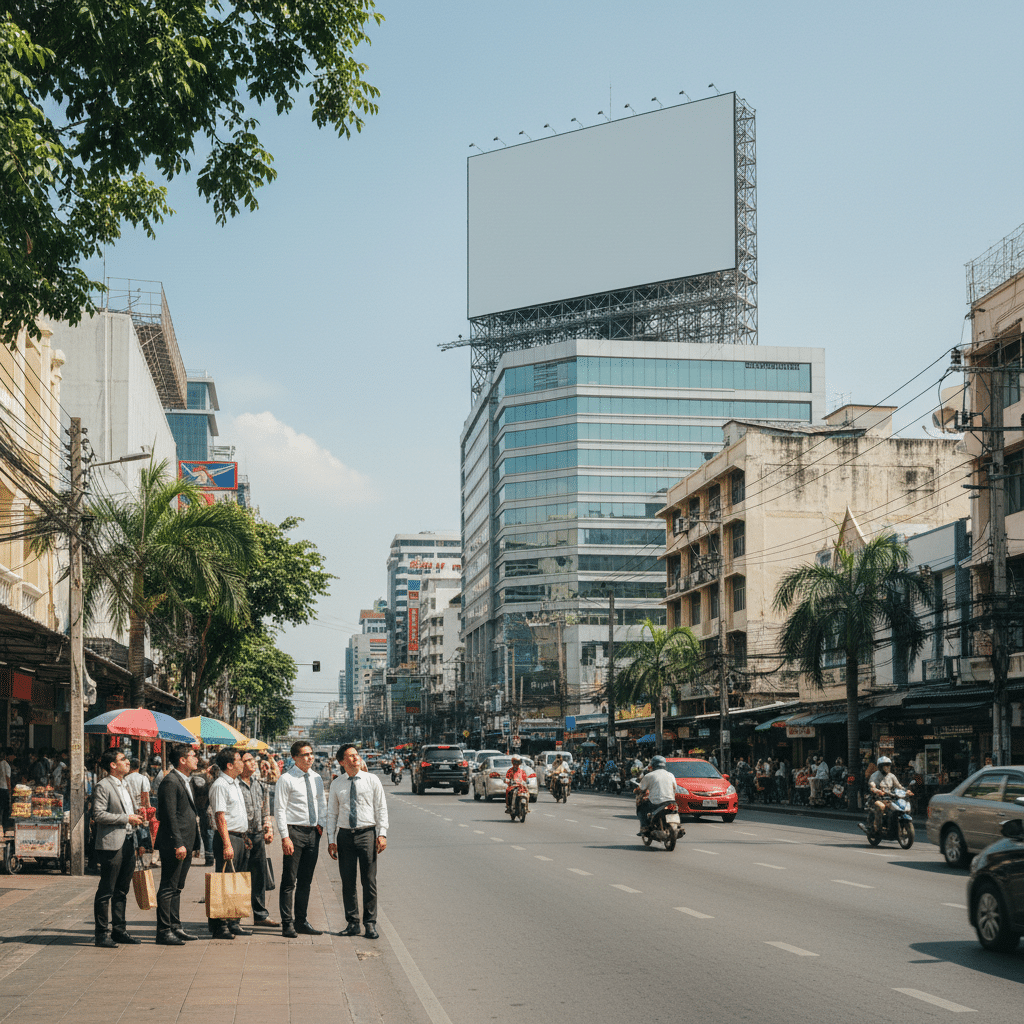
ขนาดตัวอักษรป้ายโฆษณา ต้องใหญ่แค่ไหนถึงมองเห็นชัด
การออกแบบสื่อสิ่งพิมพ์ โดยเฉพาะป้ายโฆษณา ถือเป็นหัวใจสำคัญของการสื่อสารทางการตลาดสำหรับผู้ประกอบการและธุรกิจ SME การกำหนด ขนาดตัวอักษรป้ายโฆษณา ต้องใหญ่แค่ไหนถึงมองเห็นชัด เป็นคำถามพื้นฐานที่ส่งผลโดยตรงต่อประสิทธิภาพในการดึงดูดสายตาและส่งสารไปยังกลุ่มเป้าหมาย หากตัวอักษรมีขนาดเล็กเกินไป ข้อความสำคัญอาจถูกมองข้าม ในทางกลับกัน หากใหญ่เกินไปอาจทำให้องค์ประกอบโดยรวมดูไม่สวยงาม บทความนี้จะนำเสนอหลักการและข้อมูลเชิงลึกเพื่อเป็นแนวทางในการกำหนดขนาดตัวอักษรที่เหมาะสมที่สุดสำหรับป้ายโฆษณาประเภทต่างๆ เพื่อให้แน่ใจว่าทุกข้อความที่ต้องการสื่อสารจะถูกมองเห็นอย่างชัดเจนและมีประสิทธิภาพสูงสุด
สาระสำคัญของการออกแบบป้ายโฆษณา
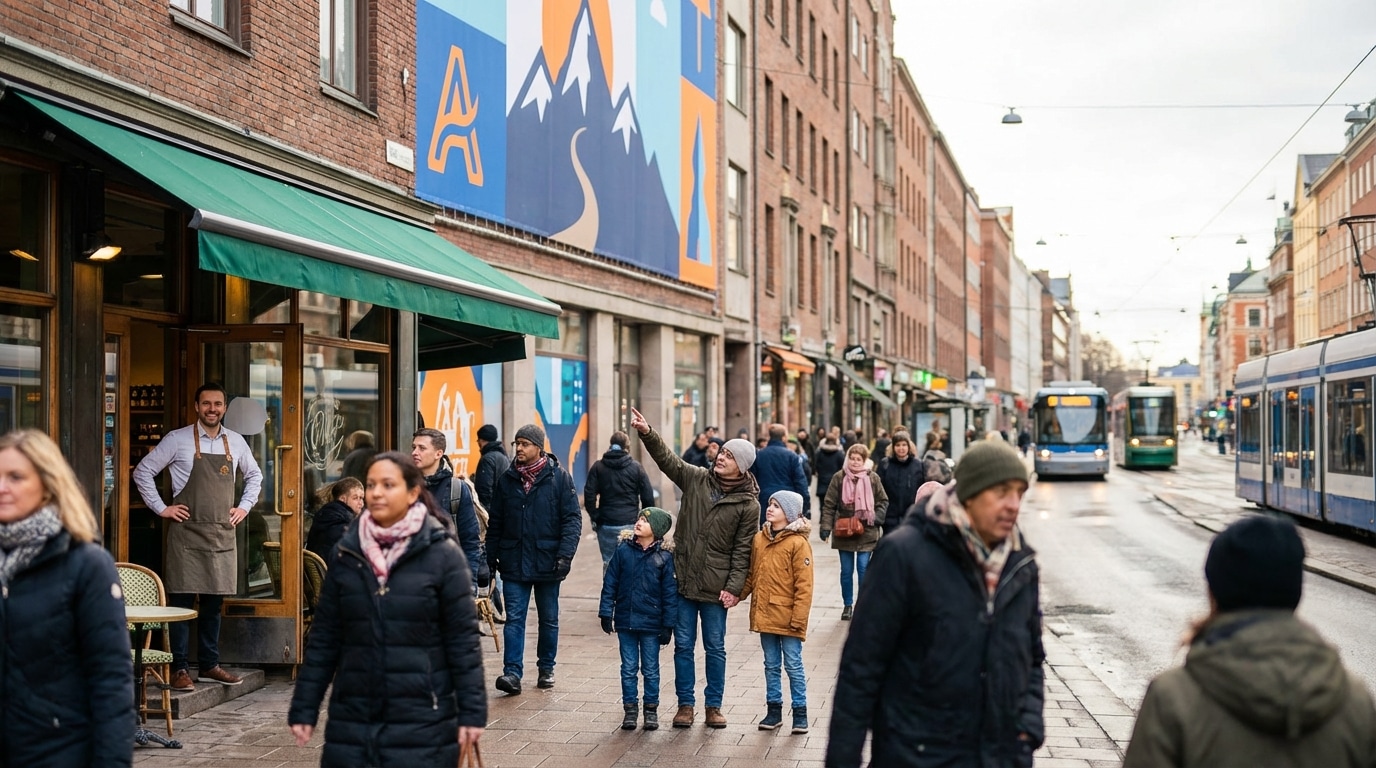
ก่อนจะลงลึกในรายละเอียดทางเทคนิค สิ่งสำคัญคือการทำความเข้าใจภาพรวมของการออกแบบป้ายโฆษณาที่มีประสิทธิภาพ ซึ่งมีประเด็นสำคัญที่ควรพิจารณาดังนี้:
- ความสัมพันธ์ระหว่างขนาดและระยะทาง: หลักการพื้นฐานที่สุดคือ ขนาดของตัวอักษรต้องสอดคล้องกับระยะทางที่ผู้ชมมองเห็น โดยมีสูตรคำนวณเบื้องต้นคือ ความสูงตัวอักษร 1 นิ้ว ต่อระยะการมองเห็น 10 ฟุต
- ความสำคัญขององค์ประกอบเสริม: นอกจากขนาดแล้ว ความคมชัดของสี (Contrast) การเลือกใช้ฟอนต์ที่อ่านง่าย แสงสว่าง และตำแหน่งการติดตั้ง ล้วนเป็นปัจจัยสำคัญที่ส่งผลต่อการมองเห็นไม่แพ้กัน
- ประเภทของป้ายกำหนดการออกแบบ: ป้ายบิลบอร์ดบนทางด่วนย่อมต้องการตัวอักษรขนาดใหญ่และข้อความที่กระชับกว่าป้ายหน้าร้านที่ผู้ชมสามารถหยุดอ่านได้ในระยะใกล้
- การวางแผนจากมุมมองของผู้ชม: การออกแบบที่ดีต้องเริ่มต้นจากการพิจารณาว่ากลุ่มเป้าหมายจะมองเห็นป้ายจากตำแหน่งใด และมีเวลาในการมองนานเท่าไร เพื่อกำหนดขนาดและจำนวนข้อความให้เหมาะสม
- ความเรียบง่ายคือหัวใจ: ป้ายโฆษณาที่มีประสิทธิภาพมักเน้นความเรียบง่าย สื่อสารข้อความหลักเพียงหนึ่งเดียวอย่างชัดเจน หลีกเลี่ยงการใส่ข้อมูลที่มากเกินความจำเป็นจนทำให้ป้ายดูรกและอ่านยาก
ไขความลับขนาดตัวอักษร และระยะการมองเห็น
การกำหนดขนาดตัวอักษรสำหรับป้ายโฆษณามิใช่เรื่องของการคาดเดา แต่เป็นศาสตร์ที่อิงหลักการทางฟิสิกส์ของการมองเห็น ปัจจัยหลักที่ต้องพิจารณาคือ “ระยะการมองเห็น” (Viewing Distance) ซึ่งหมายถึงระยะห่างระหว่างป้ายกับสายตาของผู้ชม ยิ่งผู้ชมอยู่ไกลเท่าไร ตัวอักษรก็ต้องมีขนาดใหญ่ขึ้นตามสัดส่วนเพื่อให้สามารถอ่านข้อความได้อย่างชัดเจน
สำหรับผู้ประกอบการ SME การทำความเข้าใจหลักการนี้มีความสำคัญอย่างยิ่ง เพราะช่วยให้การลงทุนในการทำป้ายไวนิลหรือป้ายโฆษณาประเภทอื่นๆ คุ้มค่าและบรรลุวัตถุประสงค์ทางการตลาด การเลือกขนาดที่ไม่เหมาะสมอาจทำให้ป้ายที่ออกแบบมาอย่างสวยงามไม่สามารถสื่อสารกับลูกค้าเป้าหมายได้เลย
สูตรคำนวณขนาดตัวอักษรพื้นฐาน
ในวงการออกแบบป้ายโฆษณามีหลักการคำนวณที่เป็นที่ยอมรับในระดับสากล เพื่อใช้เป็นแนวทางเบื้องต้นในการกำหนดความสูงของตัวอักษร ซึ่งมีอยู่สองสูตรหลักๆ ได้แก่:
- สูตรมาตรฐาน (1 นิ้ว ต่อ 10 ฟุต): นี่คือสูตรที่นิยมใช้กันอย่างแพร่หลายที่สุด หมายความว่า ทุกๆ ระยะการมองเห็น 10 ฟุต (ประมาณ 3 เมตร) ความสูงของตัวอักษรควรเพิ่มขึ้น 1 นิ้ว (ประมาณ 2.54 เซนติเมตร) สูตรนี้เหมาะสำหรับป้ายที่ต้องการให้อ่านได้ชัดเจนในสภาวะปกติ
ตัวอย่าง: หากต้องการให้ป้ายสามารถอ่านได้จากระยะ 60 ฟุต (ประมาณ 18.3 เมตร) ขนาดความสูงของตัวอักษรควรอยู่ที่ 6 นิ้ว - สูตรเพื่อความโดดเด่นสูงสุด (1 นิ้ว ต่อ 3 ฟุต): สำหรับป้ายที่ติดตั้งในบริเวณที่มีการแข่งขันสูง เช่น บนทางด่วน หรือในย่านการค้าที่เต็มไปด้วยป้ายจำนวนมาก การใช้สูตรนี้จะช่วยให้ตัวอักษรมีขนาดใหญ่และโดดเด่นสะดุดตาเป็นพิเศษ ทำให้ผู้ชมสามารถรับรู้ข้อความได้อย่างรวดเร็วแม้จะมองเพียงแวบเดียว
การเลือกใช้สูตรใดขึ้นอยู่กับบริบทและวัตถุประสงค์ของป้ายโฆษณานั้นๆ การพิจารณาสภาพแวดล้อมจริงของสถานที่ติดตั้งจึงเป็นสิ่งที่ไม่ควรมองข้าม
ตารางอ้างอิงขนาดตัวอักษรเทียบกับระยะทาง
เพื่อให้เห็นภาพที่ชัดเจนยิ่งขึ้น ตารางด้านล่างนี้เป็นการสรุปขนาดความสูงของตัวอักษรที่แนะนำตามระยะการมองเห็นต่างๆ โดยอ้างอิงจากสูตรมาตรฐาน (1 นิ้ว : 10 ฟุต) ซึ่งสามารถใช้เป็นข้อมูลอ้างอิงเบื้องต้นในการออกแบบป้ายไวนิลและสื่อโฆษณาอื่นๆ ได้
| ระยะการมองเห็น (ฟุต) | ระยะการมองเห็น (เมตร โดยประมาณ) | ขนาดความสูงตัวอักษรที่แนะนำ (นิ้ว) |
| 10 ฟุต | 3 เมตร | 1 นิ้ว |
| 30 ฟุต | 9.1 เมตร | 3 นิ้ว |
| 50 ฟุต | 15.2 เมตร | 5 นิ้ว |
| 100 ฟุต | 30.5 เมตร | 10 นิ้ว |
| 200 ฟุต | 61 เมตร | 20 นิ้ว |
| 400 ฟุต | 122 เมตร | 40 นิ้ว |
| 600 ฟุต | 183 เมตร | 60 นิ้ว |
ขนาดป้ายมาตรฐานและผลกระทบต่อการออกแบบ
ขนาดโดยรวมของป้ายโฆษณามีความสัมพันธ์โดยตรงกับขนาดตัวอักษรที่สามารถใช้ได้ ป้ายขนาดใหญ่ย่อมมีพื้นที่ให้ใช้ตัวอักษรขนาดใหญ่ได้มากขึ้น ซึ่งส่งผลให้มองเห็นได้จากระยะไกลขึ้น การทำความเข้าใจขนาดมาตรฐานของป้ายแต่ละประเภทจึงเป็นสิ่งจำเป็น
ป้ายบิลบอร์ดขนาดใหญ่
ป้ายบิลบอร์ดมักติดตั้งอยู่ริมถนนหรือทางด่วน มีขนาดใหญ่ตั้งแต่ 20 ถึง 60 ตารางเมตร หรือมากกว่านั้น กลุ่มเป้าหมายคือผู้ที่สัญจรด้วยความเร็วสูง ทำให้มีเวลาในการมองและอ่านข้อความเพียงไม่กี่วินาที ดังนั้น การออกแบบป้ายบิลบอร์ดจึงต้องคำนึงถึงสิ่งต่อไปนี้:
- ตัวอักษรขนาดใหญ่พิเศษ: ต้องใช้ขนาดตัวอักษรที่ใหญ่มากเพื่อให้มองเห็นได้ชัดเจนจากระยะไกลและขณะเคลื่อนที่เร็ว
- ข้อความสั้นกระชับ: ควรมีข้อความไม่เกิน 5-7 คำ เพื่อให้สามารถอ่านจบได้ในครั้งเดียว
- เน้นภาพและแบรนด์: ใช้ภาพกราฟิกที่น่าสนใจและแสดงชื่อแบรนด์หรือโลโก้ให้เด่นชัดที่สุด
ป้ายหน้าร้านค้าและอาคาร
ป้ายประเภทนี้มีขนาดเล็กลงมา โดยทั่วไปอยู่ที่ 2-10 ตารางเมตร ติดตั้งในระดับสายตาหรือสูงกว่าเล็กน้อย ผู้ชมมักเป็นคนเดินเท้าหรือผู้ที่ขับรถช้าๆ ในบริเวณนั้น ซึ่งมีเวลาในการพิจารณาป้ายมากกว่าป้ายบิลบอร์ด หลักการออกแบบจึงแตกต่างออกไป: